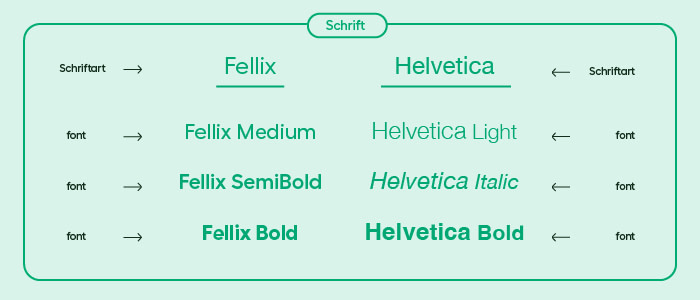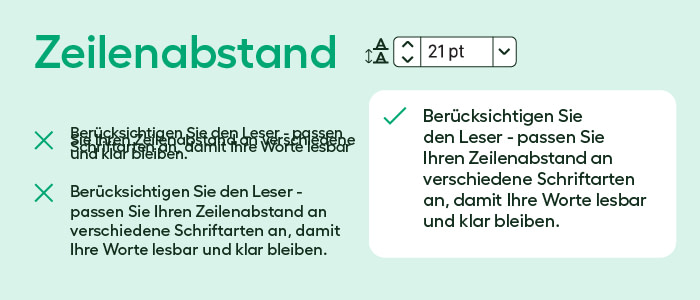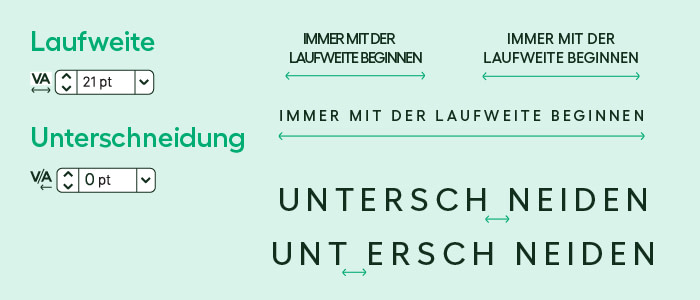
MOOs Design-Tipps: Typografie
Wenn Schriftgestaltung für Sie Neuland ist oder Sie einfach ein paar nützliche Tipps brauchen, um Ihre Ästhetik zu verbessern, können wir Ihnen helfen.
Wer könnte Fragen zur Typografie besser beantworten als Grafikdesigner? Wir haben uns mit MOOs Kreativteam zusammengesetzt, um den Jargon zu erklären und Ihnen ein paar hilfreiche Tipps zur Optimierung Ihrer Designs zu geben.
Was ist der Unterschied zwischen Satzschrift, Schriftart und Font?
Die Terminologie rund um Typografie ist komplex, wobei die Wörter Font und Schriftart oft austauschbar verwendet werden. Hier ist kurz zusammengefasst, was die Hauptbegriffe bedeuten:
Schriftart: auch ‘Schriftfamilie’ genannt. Dies ist der Begriff für das einzigartige Design einer individuellen Schrift, z.B. Helvetica.
Font: Das Gewicht und die Größe einer Schriftart, z.B. Helvetica Light Oblique and Helvetica Bold. Beide gehören zur Helvetica-Schriftfamilie, da sie auf dem gleichen Design basieren.
Satzschrift: Der Oberbegriff, der alle Fonts und Schriftarten umfasst.
So, nachdem die Grundbegriffe geklärt sind, wie sieht’s nun mit dem Design aus?
Wählen Sie Ihre Schriftgröße
Wie groß muss mein Font sein?
„Die Worte Ihrer Marke können an allen möglichen verschiedenen Stellen erscheinen, von der Plakatwand bis zur Rückseite einer Visitenkarte“, erklärt Millie, unsere Designchefin, „also ist die Größe der Fläche, auf der die Buchstaben stehen, maßgeblich dafür, wie groß sie sein können. Die Schriftart, die Sie nutzen, bestimmt auch, wie leicht sie zu lesen ist. Leichte Fonts wie Helvetica Neue UltraLight müssen größer gedruckt werden als schwerere, wie z.B. Franklin Gothic, um lesbar zu sein.
Wahl der richtigen Schriftgröße für Drucksachen
Laut MOOs Grafikdesignerin Emilt Wheeler sollten Ihre Visitenkarten eine Schriftgröße von mindestens 7pt haben, während gedruckte AGB nicht kleiner als 6pt sein sollten. Text auf Flyern und Postkarten sollte in der Regel ebenfalls 7pt groß sein.
Wie beeinflussen verschiedene Schriftarten die Fontgröße?
Die Schriftart und der Font, die Sie wählen, bestimmen auch, wie groß die Schrift gedruckt werden sollten. Wenn Sie z.B. eine Hochzeitseinladung gestalten, wählen Sie vielleicht eine aufwendige Skriptschrift, um die Namen hervorzuheben. In diesem Fall müssten Sie in einer viel größeren Schriftgröße drucken, damit sie lesbar ist. Kleinere Details, die leicht lesbar sein müssen, wie z.B. das Venue und die Zeit, könnten in einem klareren Font gedruckt werden, der kleiner sein kann.
Die schnellen Schrift-Tipps unserer Designer
- Klare, schlichte Schriftarten funktionieren oft besser für korporative Unternehmen, während kreative oder handwerkliche Betriebe sich etwas Ausdrucksvolleres erlauben können.
- Sie können Schrift auch als grafisches Element einsetzen. Auf einer Visitenkarte können Sie z.B. größere Initialen als Hintergrund drucken und kleineren, kontrastierenden Text darauf setzen. Dies erzeugt einen dynamischen, spielerischen Effekt.
Buchstaben mit Unterlänge
Was sind Buchstaben mit Unterlänge?
Die unsichtbare Linie, auf der Ihre Schrift sitzt, wird als Grundlinie bezeichnet. Buchstaben mit Unterlänge sind alle Buchstaben, die nach unten über die Grundlinie hinausragen, z.B. ‘‘g’, ’y’, ’j’ und ‘p’. Buchstaben mit Oberlänge dagegen sind die Zeichen, die über die sogenannte ‘x-Höhe’ hinausragen, wie z.B. ‘k’, ’l’ und ‘b’. Die x-Höhe ist die Höhe der Kleinbuchstaben ohne Ober- oder Unterlänge, wie ‘a’, ’c’ und ‘x’.
Warum müssen Sie sie berücksichtigen?
„Es ist wichtig, auf Buchstaben mit Unterlänge zu achten“, erklärt Grafikdesignerin Em Stokes. „Wenn Sie z.B. einen Flyer gestalten, werden Sie eine Menge Text verwenden, also müssen Sie aufpassen, dass die Ober- und Unterlängen auf jeder Linie sich nicht berühren. Sonst kann es sehr unsauber und unleserlich aussehen.“ Um Ihren Linien mehr Raum zu geben, müssen Sie den Durchschuss anpassen.
Was ist der Durchschuss?
Der Durchschuss ist der Freiraum zwischen zwei Grundlinien in Textzeilen. Wenn der Durchschuss zu schmal ist überlappt die Unterlänge (der ‘Schwanz’ von einem ‘j’ oder ‘g’) die darunterstehenden Buchstaben.
Können verschiedene Schriftarten die Unterlänge beeinflussen?
In der Typografie gibt es keine Standardabstände. Jede Schriftart hat ein einzigartiges Design, einige mit längeren Ober- und Unterlängen als andere. Längere Schriftarten brauchen natürlich mehr Platz.
Schnelle Schrift-Tipps unserer Designer
- Denken Sie an den Leser – passen Sie Ihren Zeilenabstand den unterschiedlichen Schriftarten an, um Ihren Text leserlich und klar zu halten.
- Nehmen Sie die optimale Anpassung vor, indem Sie Ihren Zeilenabstand in der Symbolleiste Ihres Illustrator- oder InDesign Programms einstellen.
Was bedeuten Laufweite und Kerning?
Was ist Laufweite?
Laufweite ist die Bezeichnung für den Abstand zwischen den Buchstaben in einem Wort. Wenn Sie die Laufweite in Ihrem Design- oder Illustrationsprogramm einstellen, wird es das ganze Wort gleichmäßig spationieren. Das Problem dabei ist, dass in bestimmten Schriftarten einige Buchstaben zu nah an einem Nachbarn und zu weit entfernt vom anderen erscheinen können. Hier kommt Kerning ins Spiel.
Was ist Kerning?
Laufweite spationiert die Buchstaben in einem Wort gleichmäßig, während Kerning die Technik bezeichnet, Abstände zwischen individuellen Buchstaben manuell zu ändern. Dies ist hilfreich bei manchmal kniffligen Buchstaben wie ‘r’.
Erzeugen Sie Effekte mit der Laufweite
„Die Einstellung der Laufweite ist nicht unbedingt nur eine praktische Technik“, sagt MOOs Grafikdesigner Phil. „Man kann auch stilistische Effekte damit erzielen. Wenn Sie die Überschrift für einen Flyer gestalten, könnten Sie durch Anpassung der Laufweite die Buchstabenabstände vergrößern, um sie leichter lesbar zu machen und Aufmerksamkeit zu erregen.“ Wenn Ihr Branding eine modernere, klare Ästhetik hat, können Sie schmalere Schriftarten weiter spationieren, um dies zu reflektieren.“
Die schnellen Schrift-Tipps unserer Designer
- Stellen Sie immer zuerst die Laufweite ein – Kerning können Sie, falls nötig, vornehmen, nachdem die Buchstaben spationiert sind,
- Ändern Sie Laufweite und Kerning nur für einen bestimmten Zweck, da die meisten Schriftarten in Programmen wie Adobe Illustrator und InDesign bereits optimiert wurden.
- Die Anpassung der Laufweite ist normalerweise nur bei Wörtern in Großbuchstaben nötig.